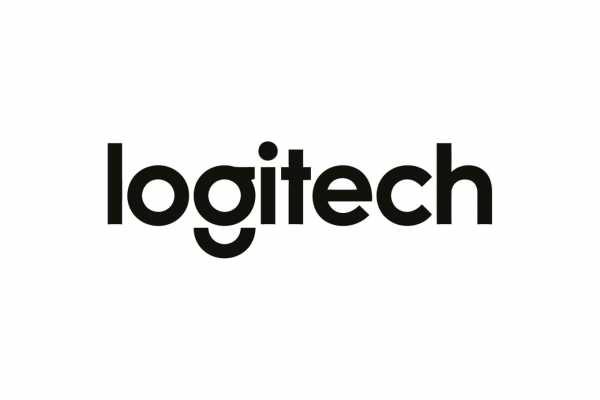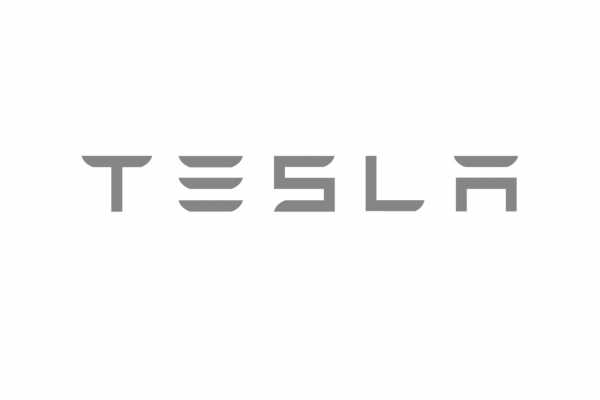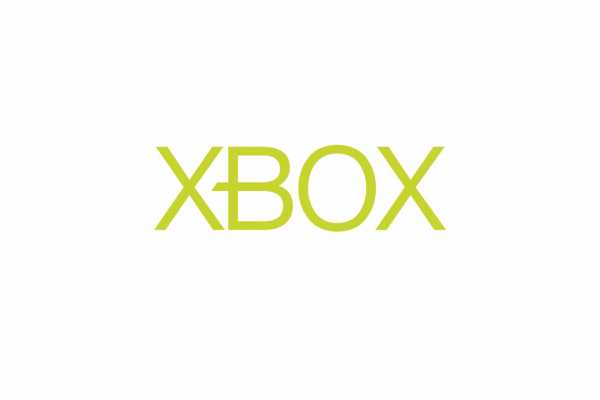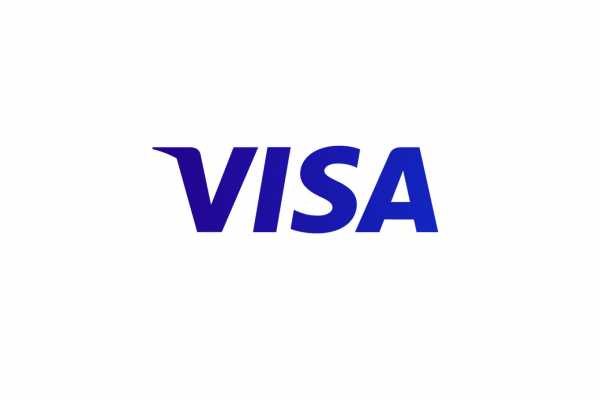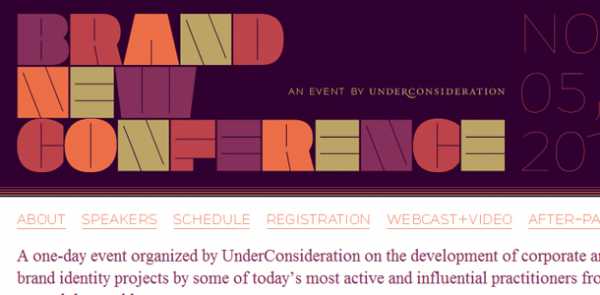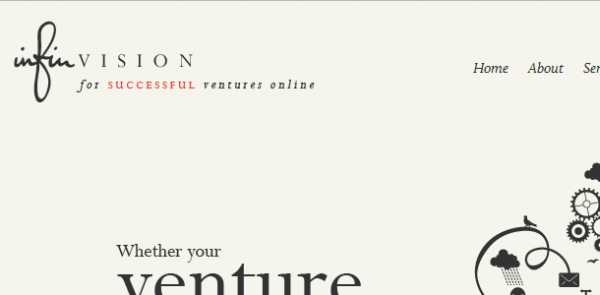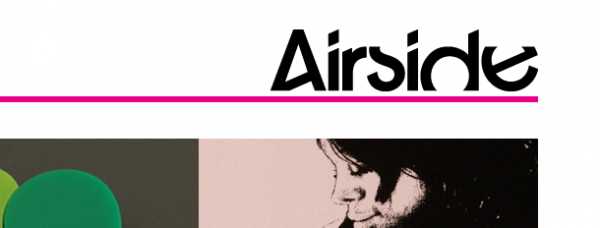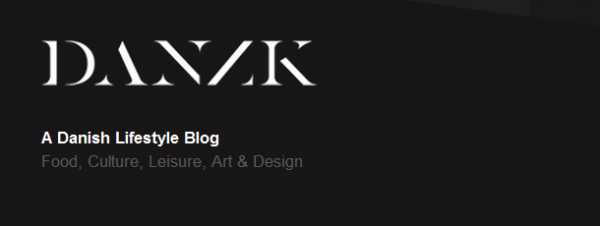
Создание и разработка шрифта для логотипа, как выбрать красивый шрифт для логотипа
Создание и разработка шрифта является невероятно важным дизайнерским процессом, который актуален в период работы над логотипом, а также фирменным стилем вашего бренда. Не секрет, что именно стилистика начертания тех или иных слов вызывает у ваших потенциальных клиентов ассоциацию непосредственно с вашей компанией, поэтому крайне важно создать шрифт запоминающимся, не загроможденным, красивым.
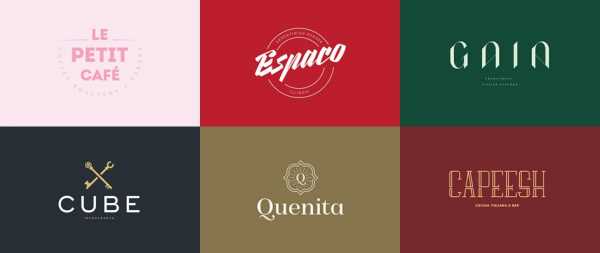
Почему так важна разработка шрифта для логотипа
Давайте рассмотрим основные причины, из-за которых к стилистике написания букв в логотипе следует отнестись с особенной внимательностью:
- Ассоциативный эффект Никакому бизнесмену не захочется, чтобы их клиенты назвали бренд «какой-то компанией с сине-зеленым оформлением». Это невероятно сильно ударяет по имиджу компании, и совершенно не вызывает ассоциативного эффекта в процессе рекламных кампаний.
- Легкость восприятия Трудночитаемые слова на такой «геральдике» не вызывают у потенциальных клиентов ничего, кроме разочарования и раздражения. Согласитесь, никому не захочется разглядывать мелкие буковки на фоне огромного изображения, или огромные символы, нарисованные с кучей ненужных декоративных дополнений.
- Важность серьезного подхода Если вы отнесетесь к разработке фирменного шрифта безответственно, то очень сильно пожалеете о том, что потратили столько денег впустую. Такая разработка стоит очень дорого, поскольку поистине качественно выполненный заказ является не только своеобразным лицом компании, но и мощным маркетинговым инструментом. В качестве доказательства вспомните лишь 1 логотип компании Coca-Cola.
В данной статье мы разберем этапы разработки шрифтов, а также рассмотрим то, нужно или не нужно использовать заведомо готовые варианты, которые без труда скачиваются из интернета.
Основные подходы к разработке и созданию красивого шрифта
Ознакомление с основными понятиями
Первое, что нужно знать – это определение самого понятия «шрифт». По сути, шрифт является набором символов и знаков, объединенных общей стилистикой, размером. Также все написанные символы оформляются в единой композиции, благодаря чему слово или словосочетание начинает выглядеть достаточно монолитно, оригинально, отлично от других стилистик. Это настоящее искусство, ведь писание букв и цифр требует не менее развитого творческого подхода, как настоящая живопись или другой вид искусства. Каллиграфия уже давно является настоящим, самостоятельным ответвлением изобразительных наук.
Важность нейминга
Вторым шагом на пути к успешной работе является понимание того, что нейминг (процесс разработки имени бренда), изображения, выбранные для размещения на логотипе и шрифт – это невероятно мощные инструменты для того, чтобы ваш продукт стал узнаваемым, запоминаемым, а главное – привлекательным для потребителя. А еще эксклюзивный шрифт, которого точно не будет больше ни у кого – это символ стабильности компании, который вызывает максимальное доверие со стороны людей. Подчеркивание имиджа и репутации играет одну из самых важных ролей в процессе развития предпринимательского дела.
Идейная составлящая
Третий шаг – это определение того, что ваша работа не должна иметь аналогов. Она производится в команде людей, которые будут готовы взяться за проект. Идейная составляющая начертания также рождается в компании приближенных лиц, и об этом мы поговорим чуть позже. Нельзя забывать о том, что шрифт должен быть, в первую очередь, подходящим. Род деятельности компании влияет на будущую работу очень сильно, поэтому решение при разработке технического задания лучше всего принимать в компании доверенных лиц. Также не стоит пренебрегать замечаниями со стороны дизайнера.
Исполнитель заказа, кстати говоря, должен быть человеком, мнению которого вы доверяете. Именно поэтому следует тщательно отнестись к поиску профессионала. Важным замечанием является то, что никогда не нужно делать выбор в сторону того, кто предлагает цену дешевле. Такая работа стоит действительно недешево, но результат вы оцените самостоятельно. Просто поверьте на слово.
Какой выбрать шрифт для логотипа? Готовые варианты
Что касается готовых шрифтов, то здесь мы можем выделить сразу несколько плюсов, и сразу несколько минусов. Давайте начнем с положительных черт данной идеи.
Преимущества готового шрифта
- Экономичность Вам не придется тратить огромное количество средств на то, чтобы заниматься самостоятельной разработкой уникального начертания. Все уже давно сделано, и готово к использованию. Достаточно лишь определиться со стилистикой, найти что-то подходящее из нескольких вариантов.
- Многообразие вариантов В интернете лежит по-настоящему колоссальное количество шрифтов, каждый из которых имеет оригинальные отличия. Изобилие выбора дает вам достаточно широкий простор для фантазии, который в итоге и скажется на создании фирменного стиля, экономя ваше время и силы.
- Простота в нахождении Вам не нужно будет тратить месяцы на то, чтобы определиться с итоговым вариантом. Все уже готово – достаточно просто начать использовать!
Хоп, случается уличная магия, и появляется знак. Изображение гор, минералов, стилизованное под орнамент северных народов. Как он появился? Сегодня говорим про шрифт, так что без обид, как-нибудь в следующих статьях. Беру в мозолистые руки фотошоп, и делаю подачу.